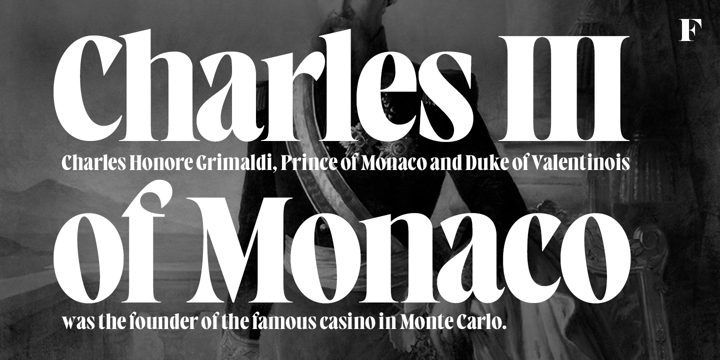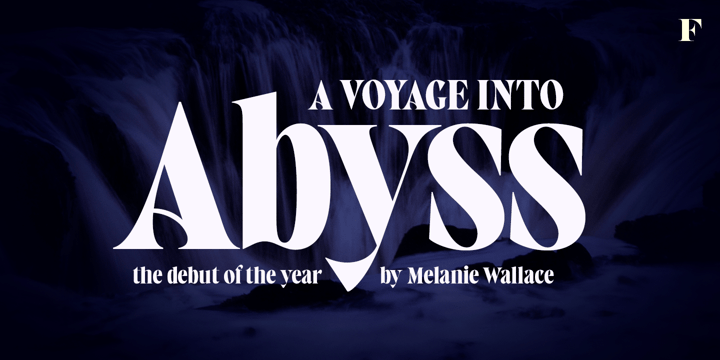
West West Font
Description de West West Font
West West est un empattement d’affichage condensé à contraste élevé. West West a une hauteur x extra large, ce qui le rend approprié pour un choix efficace pour une utilisation d’affichage distinctive telle que les titres, les emballages, les magazines, les affiches et la publicité, entre autres. Dans les grandes tailles, vous pouvez également essayer un suivi plus serré pour un impact maximal. Avec certaines formes Art Nouveau et un contraste massif, West West est un excellent choix partout où vous avez besoin d’une touche élégante et à la mode.